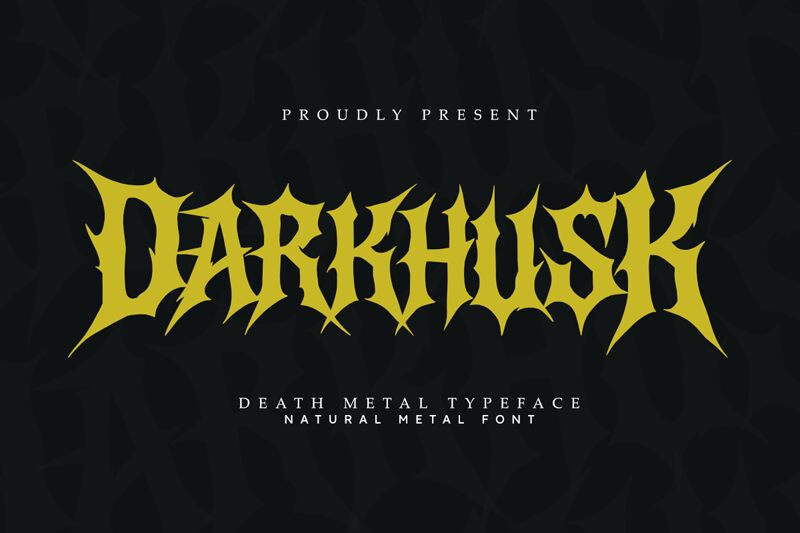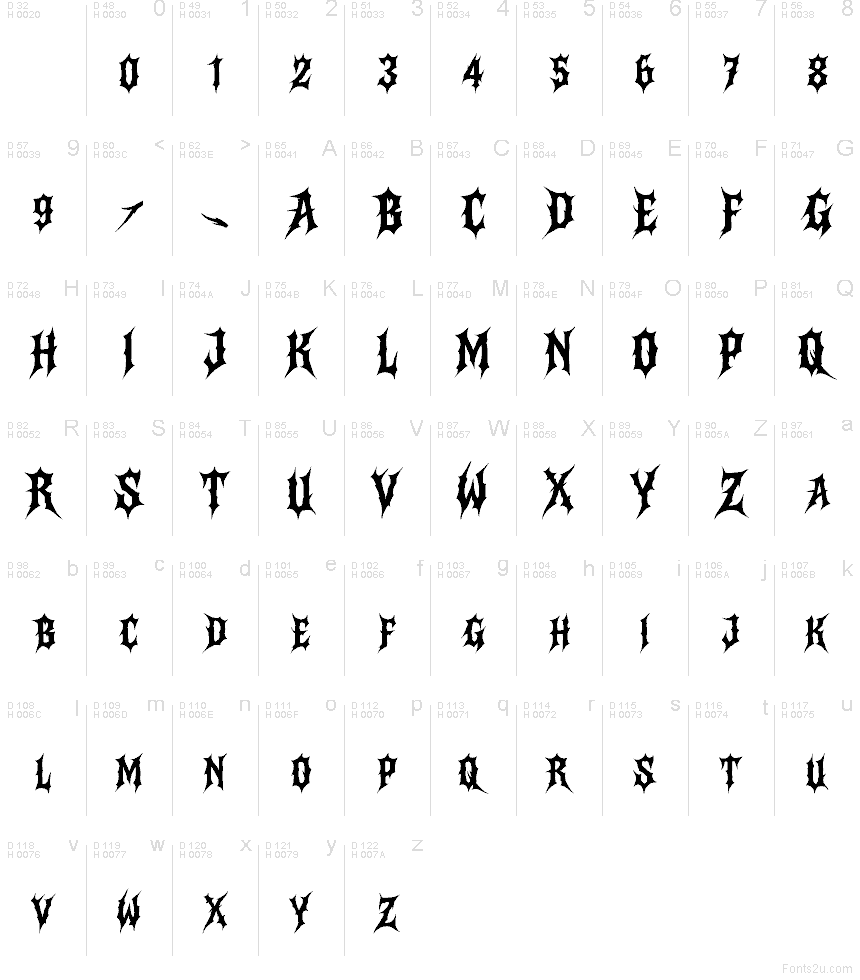
Darkhusk od Masyafi Studio je bezplatné gotické písmo s ostrými tvary typu blackletter a výraznými, prořezávanými detaily. Písmena přecházejí do úzkých hrotů a zubatých spojů, což rodině dodává drsný, tesaný dojem, aniž by ztratila svou historickou strukturu.
Darkhusk skvěle funguje na hororových plakátech, vizuálech pro tvrdou hudbu, v brandingu tetovacích studií, u dark fantasy titulů a herních log, kde dává smysl drsný středověký tón. Jeho hranatý rytmus se hodí i na obaly, letáky k akcím a dekorativní nadpisy, když chcete, aby písmo samo o sobě neslo atmosféru.